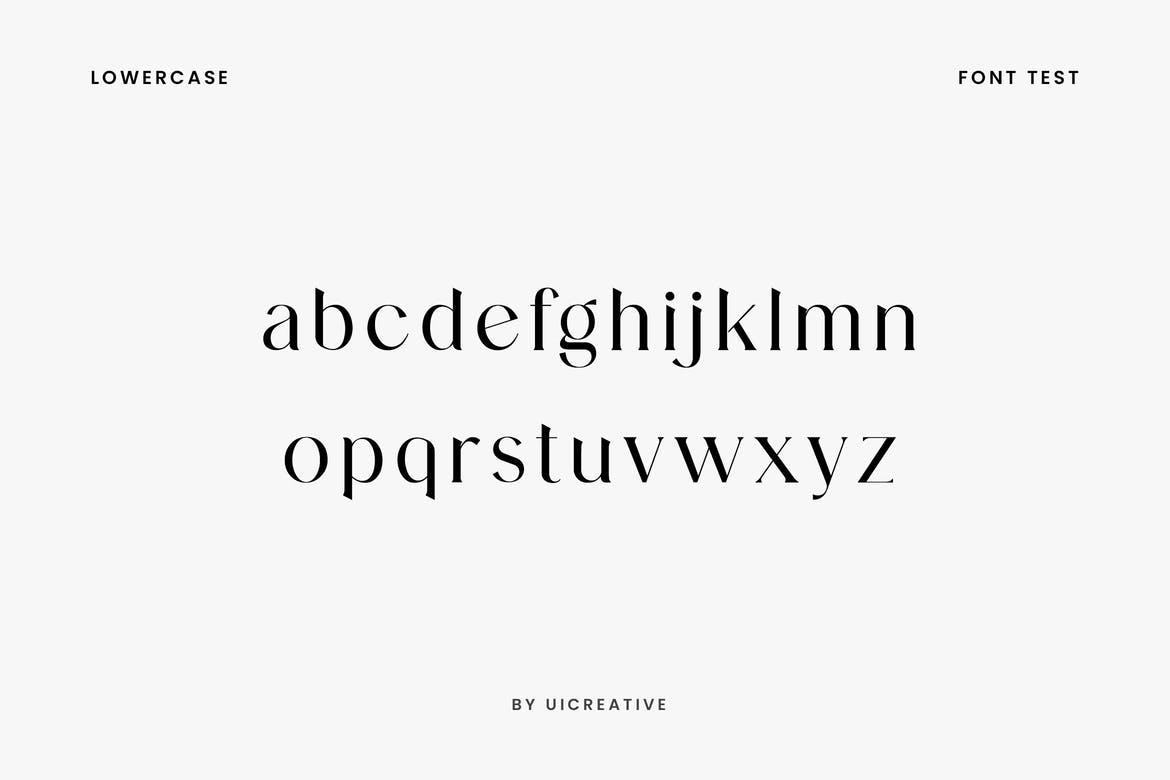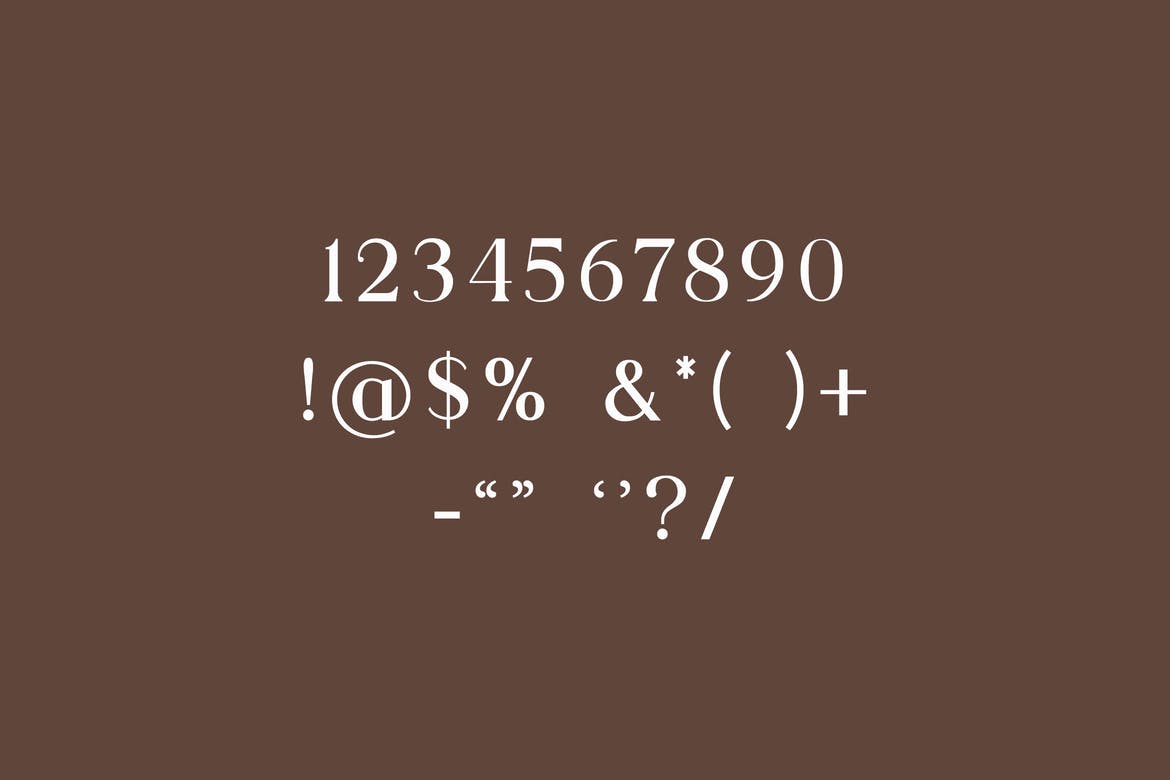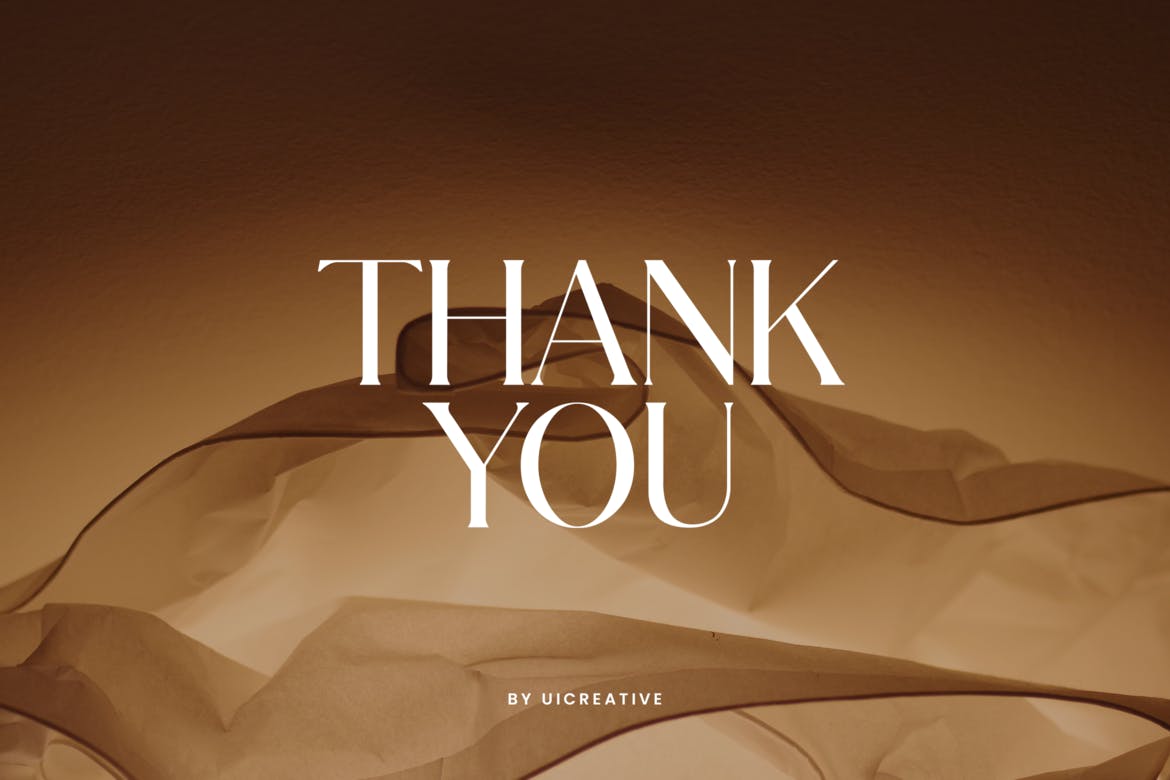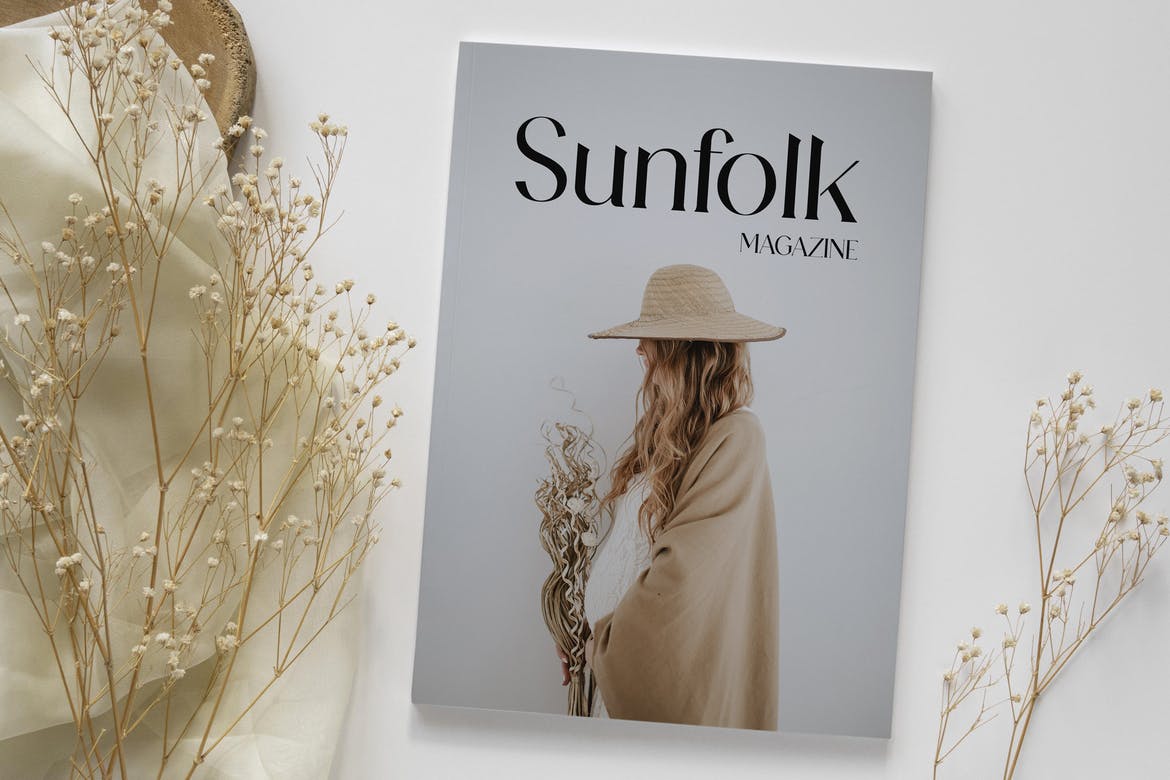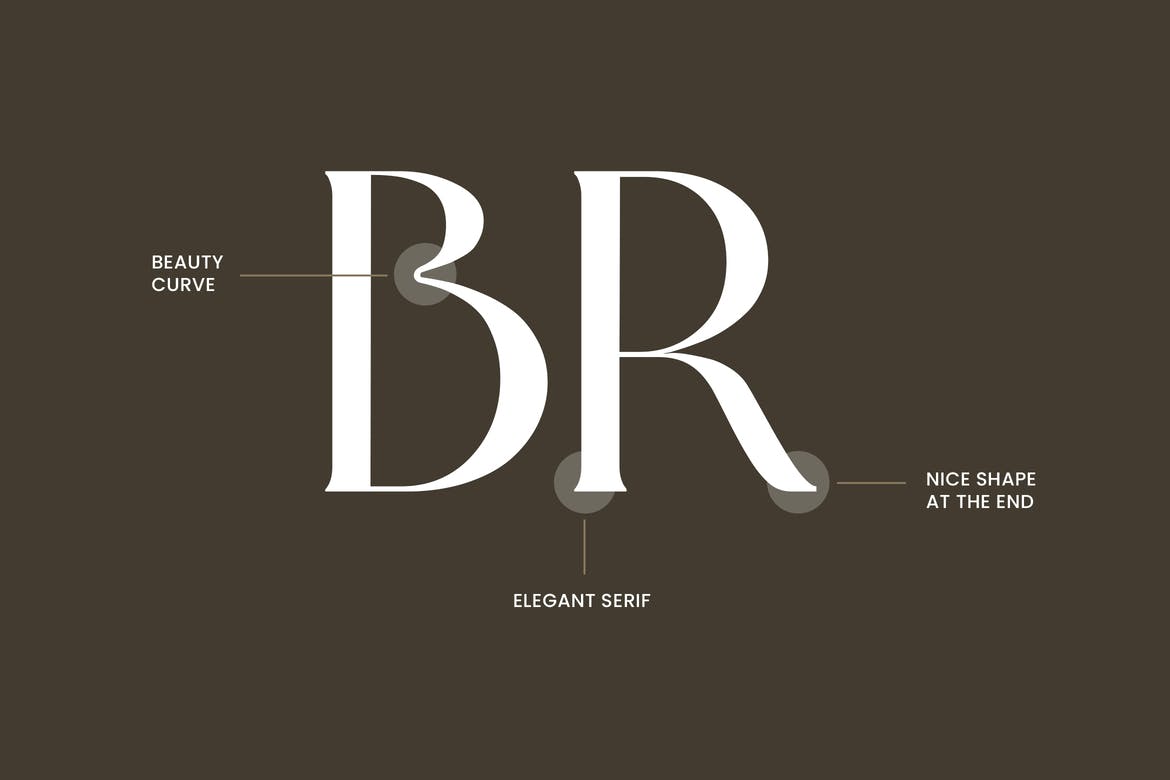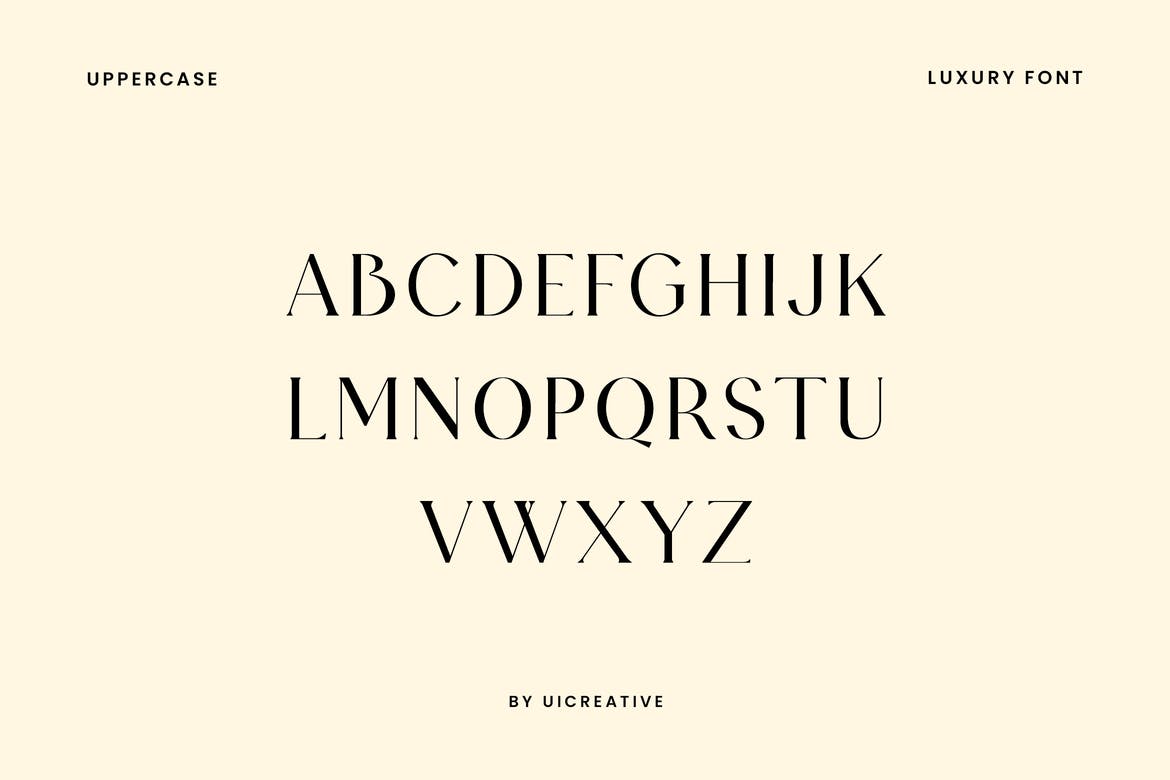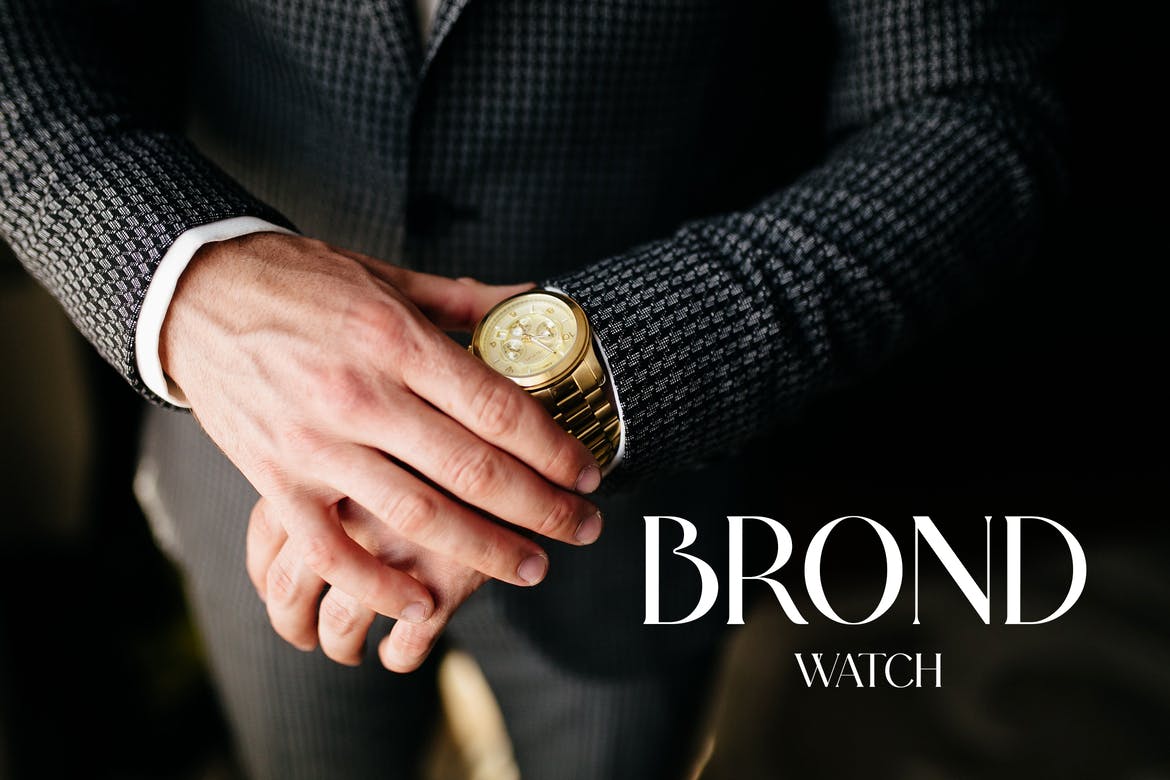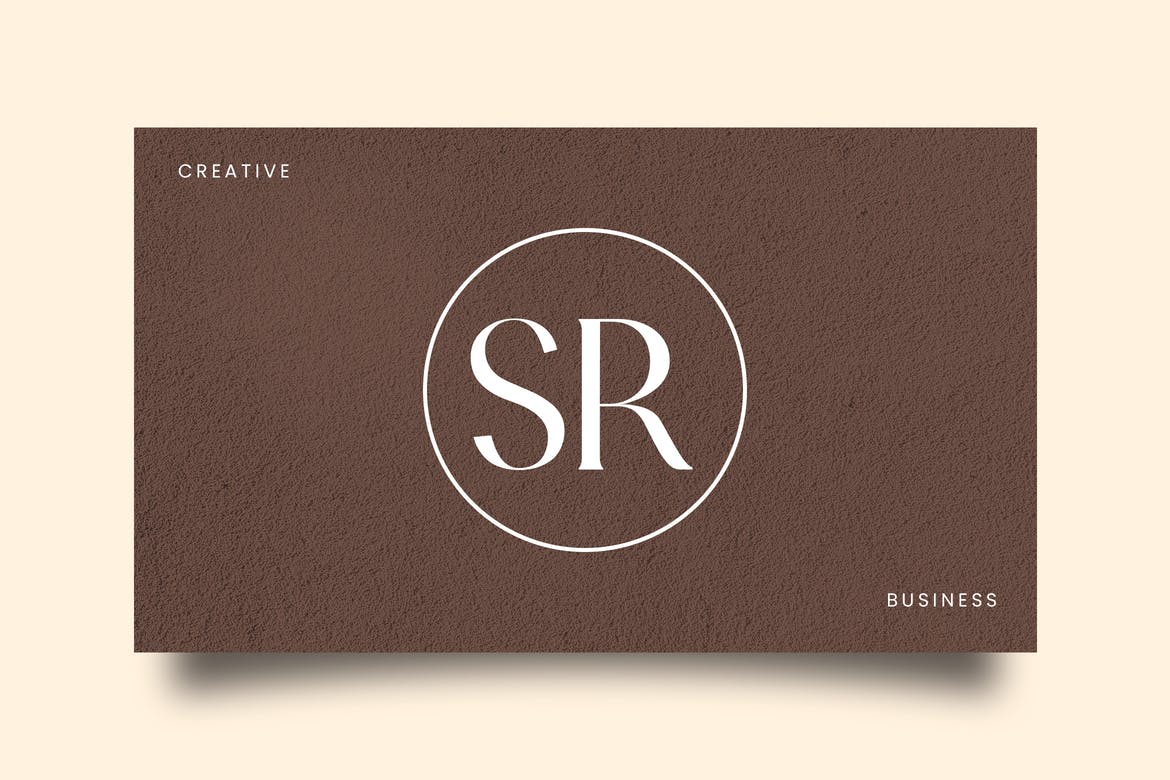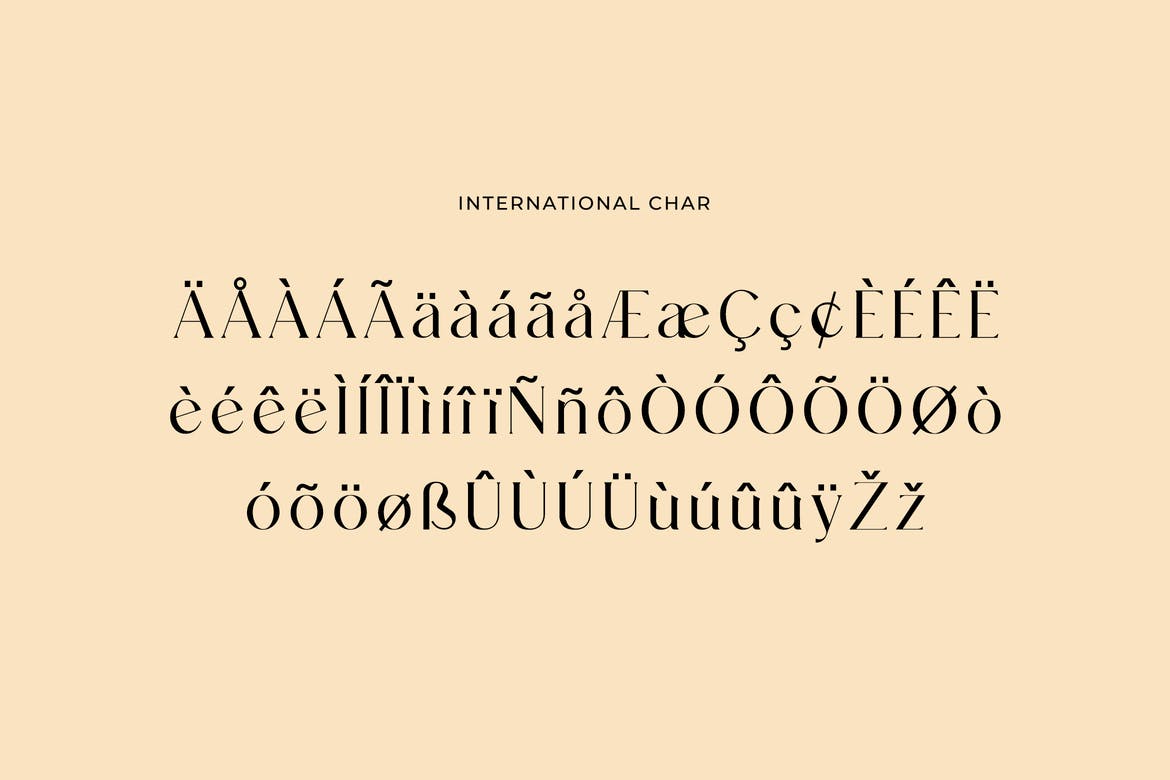
دانلود فونت لاکسیچی لوکس Serif با طراحی مدرن
Luxiachy Luxury Serif Font
فونت لاکسیچی لوکس Serif با طراحی زیبا و مدرن، مناسب برای پروژه‌های مختلف.
معرفی محصول جدید ما با نام فونت لاکسیچی لوکس Serif. این فونت سریف مدرن، حس زیبایی، کلاس و شیکی را به همراه دارد. این فونت به‌طور کامل برای انواع مختلف پروژه‌ها مناسب است، از جمله امضا، لوازم‌التحریر، لوگو، عروسی، نقل‌قول‌های تایپوگرافی، جلد مجله یا کتاب، هدر وب‌سایت، لباس، برندینگ، طراحی بسته‌بندی و موارد دیگر. همچنین، برندینگ یا طراحی ویرایشی مرتبط با مد، ویژگی‌های مردانه و زنانه را به‌طور همزمان نمایش می‌دهد.